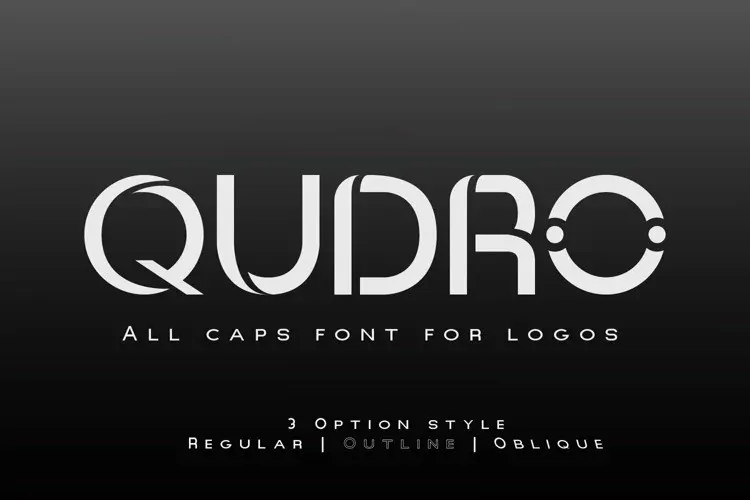
A Qudro Font é uma nova tipografia exibição criada por Irfan Hidayat. Ela tem linhas elegantes, minimalistas e clássicas, com um ar moderno que certamente faz dela uma escolha perfeita para projetos de design como títulos de filmes, identidades de marca e marcas. Seu formato sem serif torna a Qudro Font versátil o suficiente para se integrar em uma variedade de usos de design, criando um visual atraente e moderno que certamente atrairia olhares. Se você está procurando por uma fonte clara e dinâmica para seus próximos projetos de design, a Qudro Font pode ser uma ótima escolha.